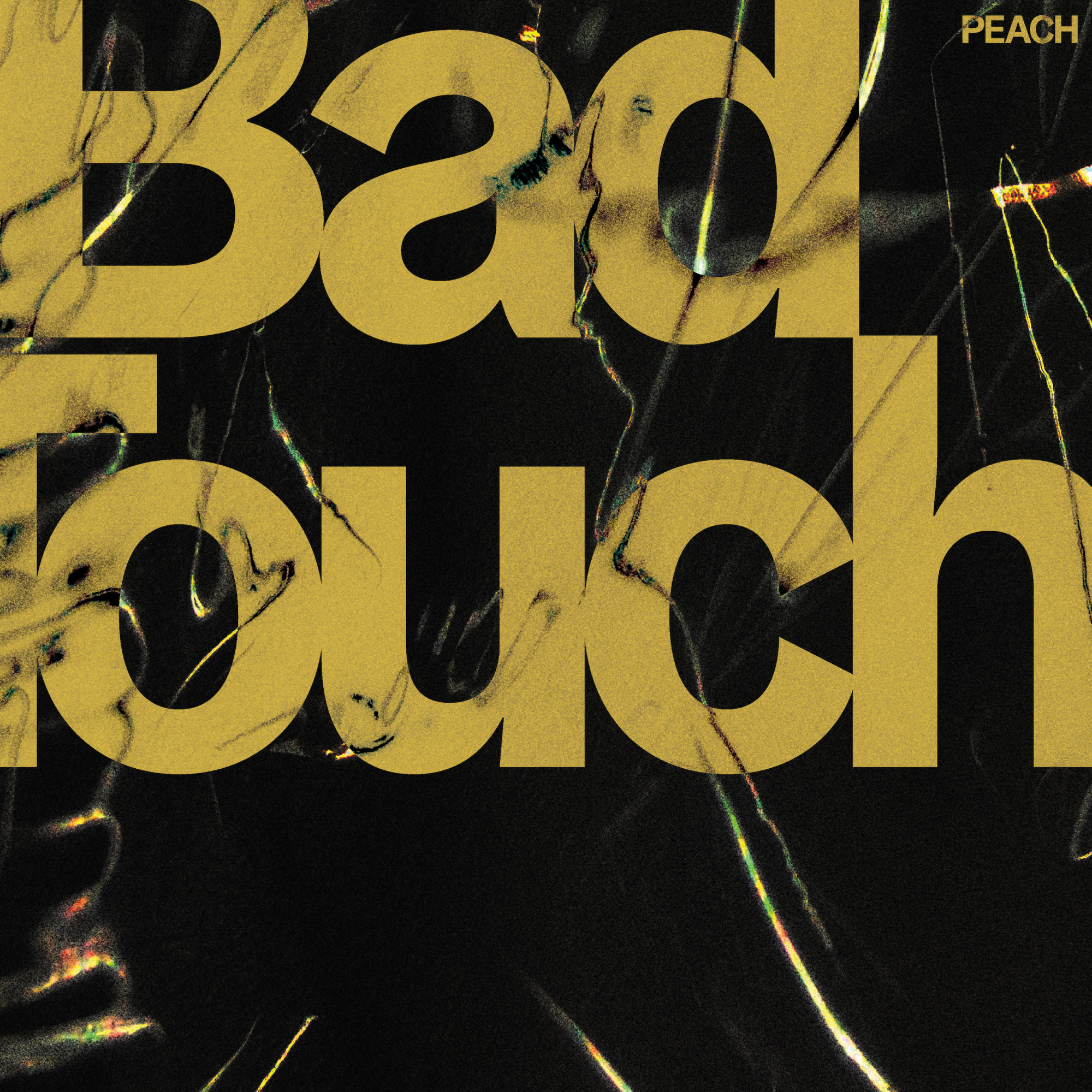
Bad Touch
Digitales Cover für die erste Single der post-punk Band Peach aus Bristol, England.
Weiche dynamische Formen werden mit harten Lichtreflexen kontrastiert, um so die Tonalität der Musik widerzuspiegeln.
Die typographische Gestaltung greift inhaltlich den Titel der Single auf, so kommen sich die Buchstaben unangenehm nah.
Schrift: Graebenbach von Camelot Typefaces